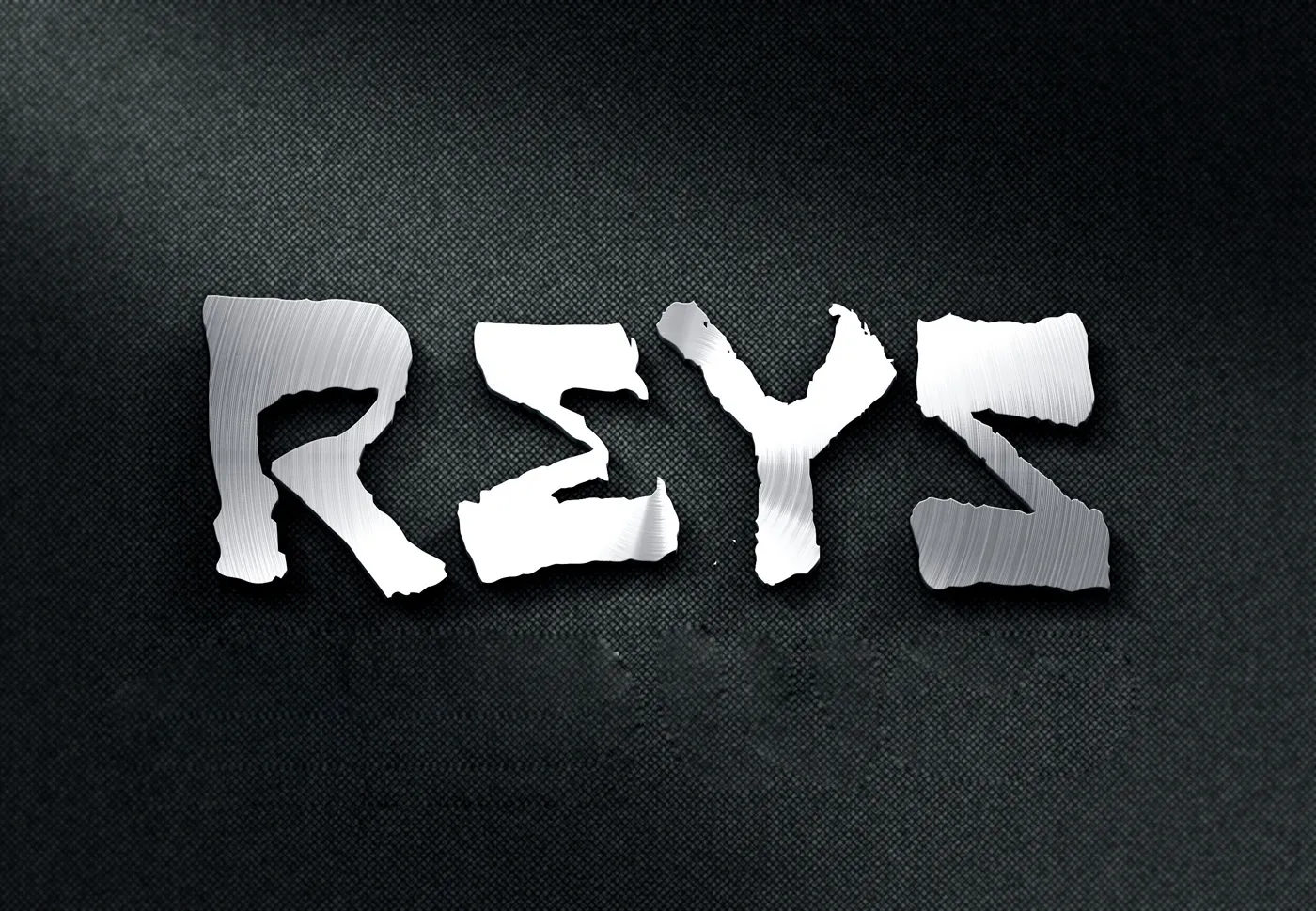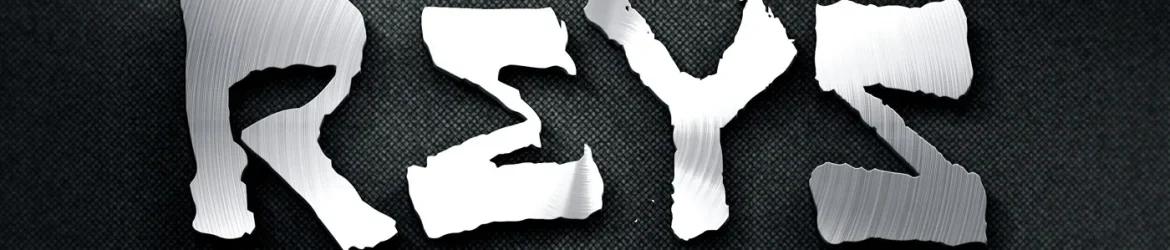
A Reys é uma fonte símbolo criada pelo designer Hamilton que traz formas simples e elegantes para ajudá-lo a criar design visual moderno e minimalista. Conectadas diretamente à natureza, as linhas retas e geométricas da Reys evocam um sentimento de simplicidade e funcionalidade, ideal para aplicações onde o foco é no conteúdo em vez da ornamentação. Seja você criando materiais informativos ou elementos gráficos minimalistas, a Reys pode complementar seu trabalho com linhas suaves que chamam atenção sem distrair. A categoria de fonte ‘Symbol Fonts’ destaca a simplicidade e eficiência dessas tipografias, o que faz da Reys uma escolha inteligente para aqueles que procuram um estilo moderno que se adapta perfeitamente a uma variedade de aplicações. Esta fonte é especialmente adequada para títulos e elementos destacados em materiais informativos ou design gráfico onde você deseja transmitir informações de maneira direta e clara, deixando o foco no conteúdo e não nas formas.